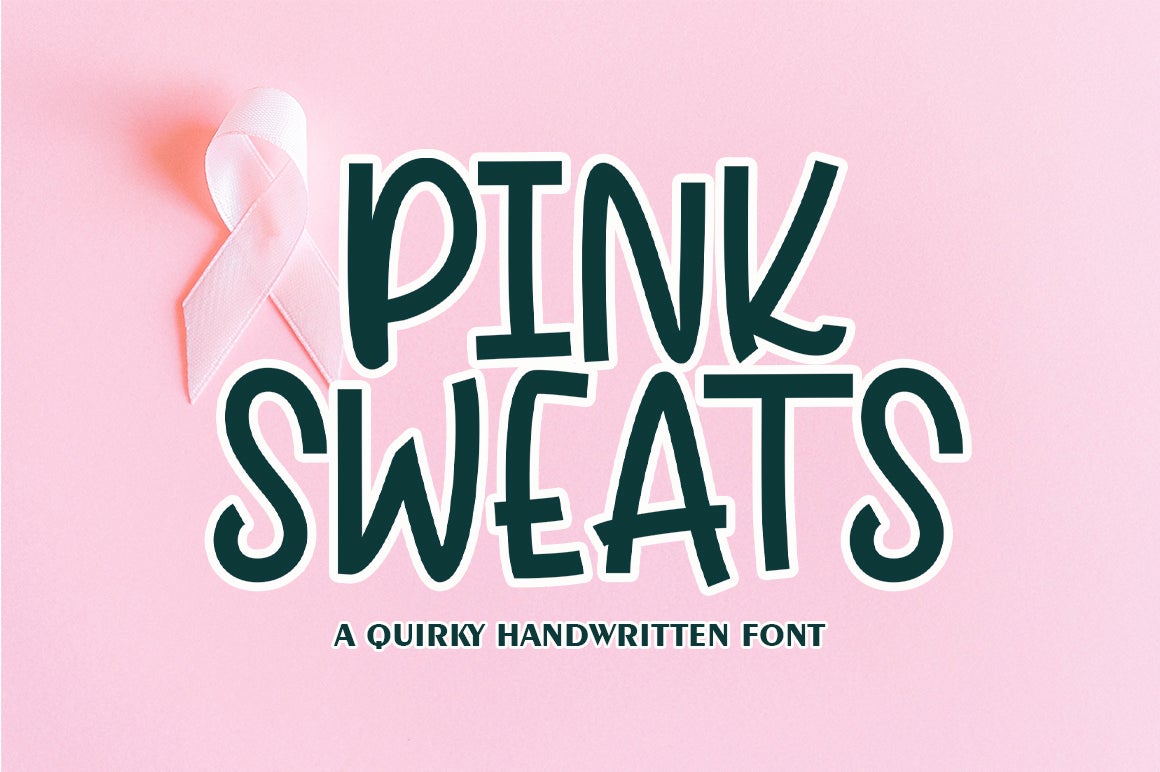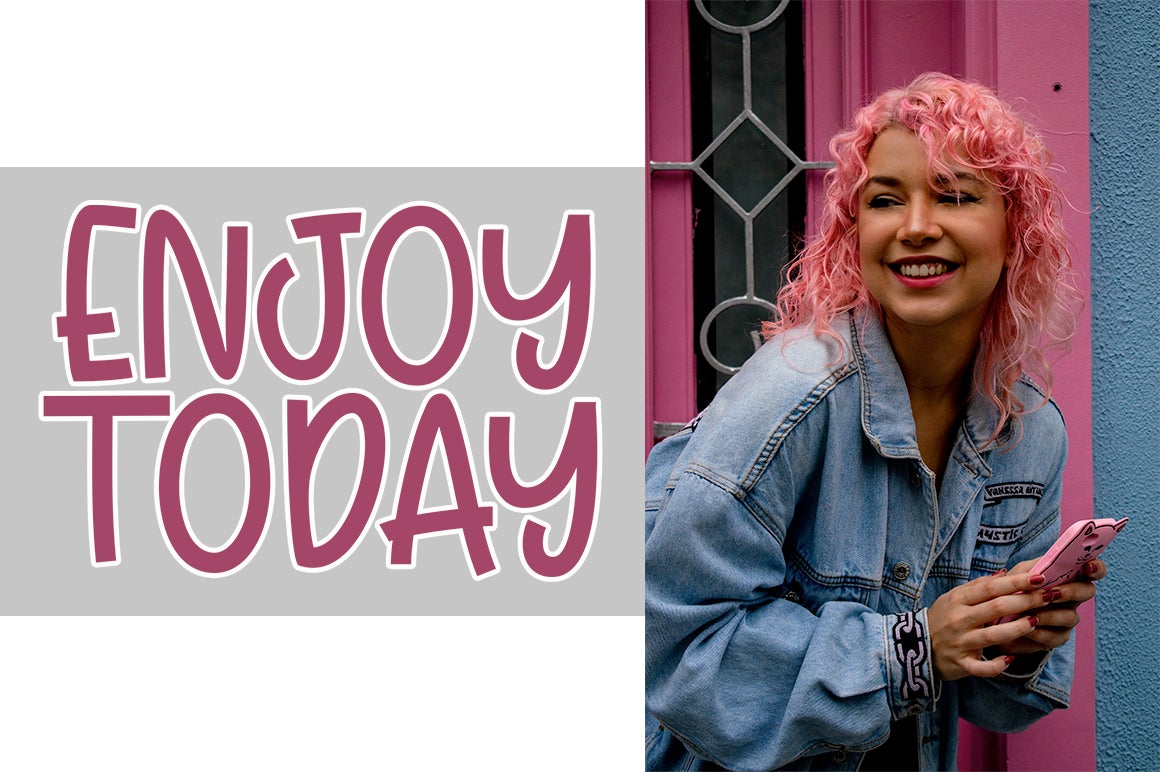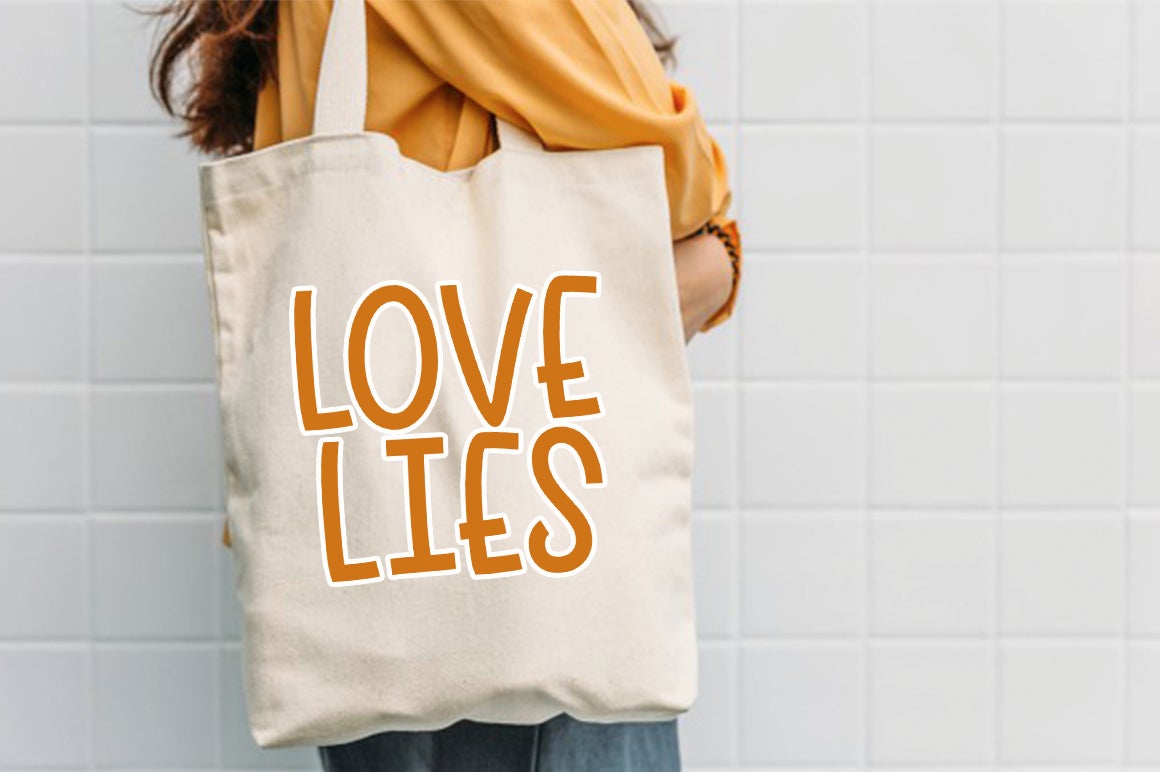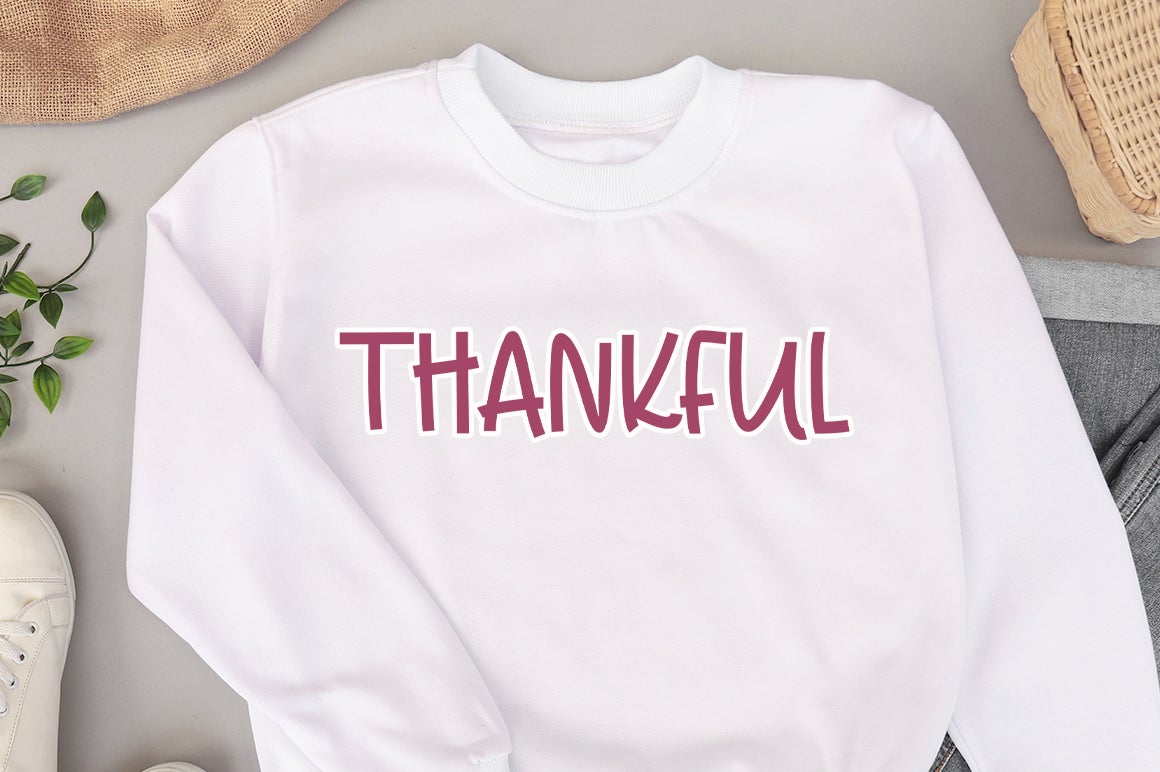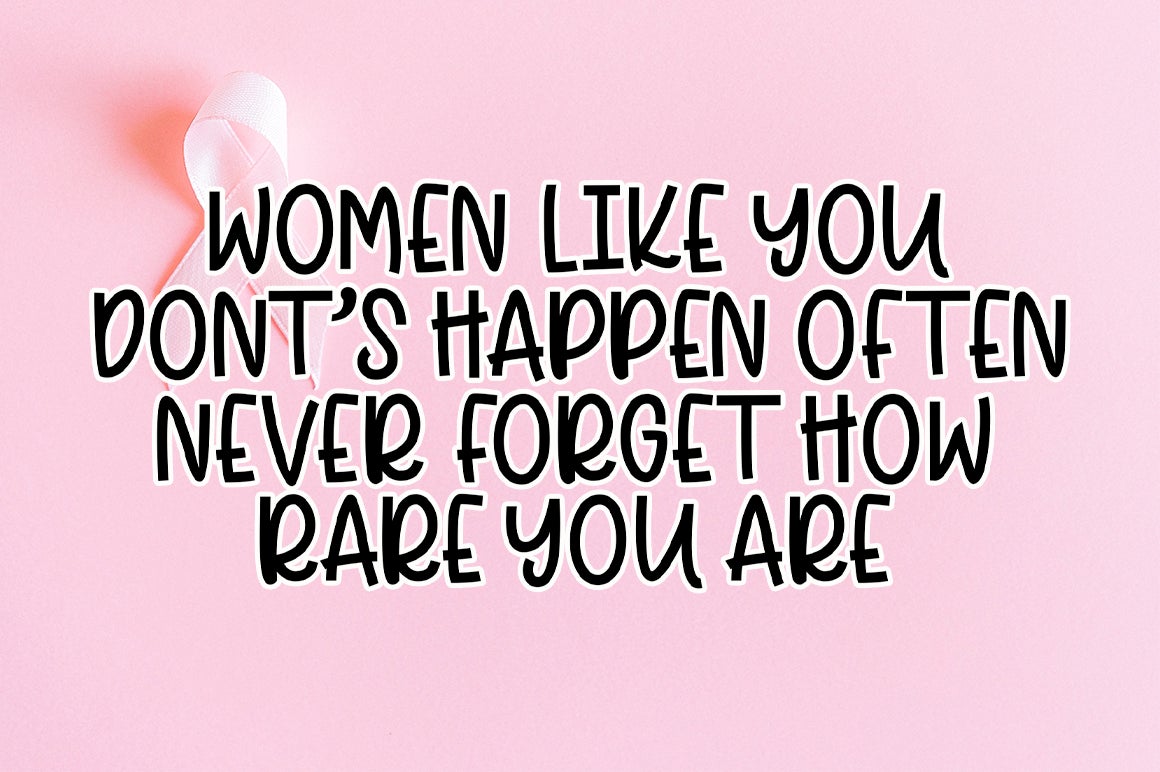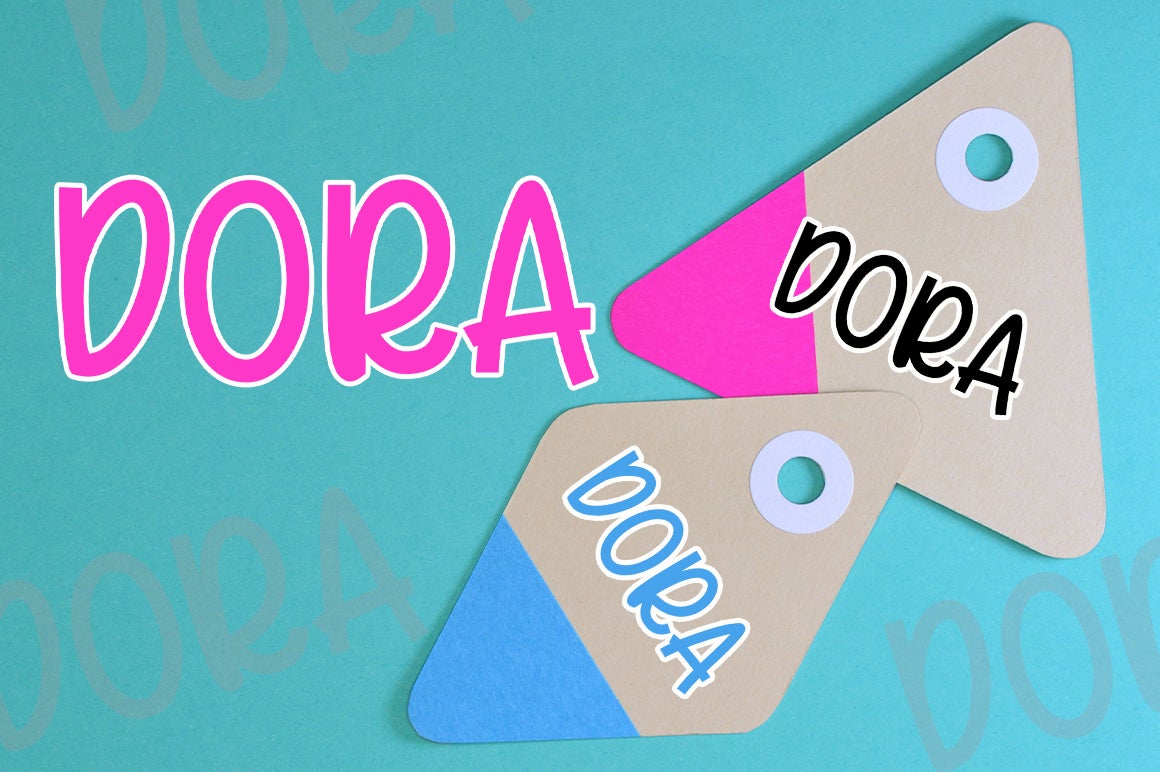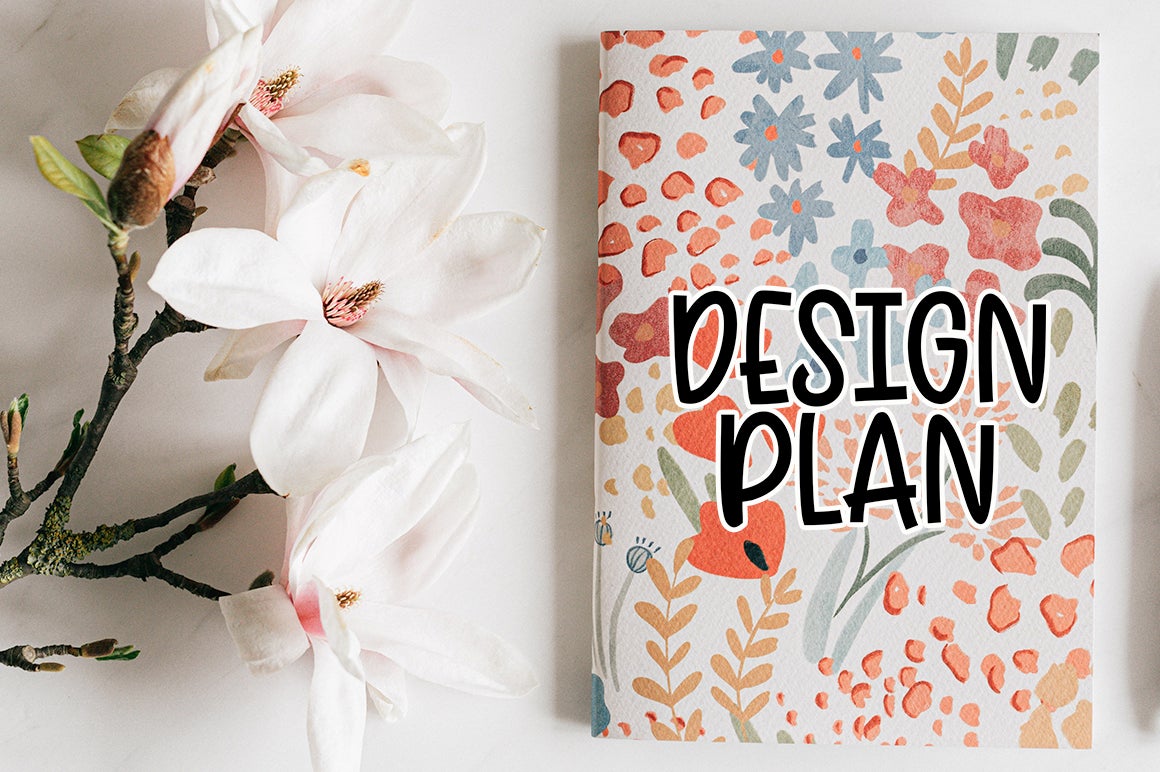
Pink Sweats adalah font tulisan tangan yang lucu, unik dan menyenangkan. Informal, santai dan ramah, font ini akan dengan mudah membuat kreasi Anda terlihat mudah didekati dan manis.